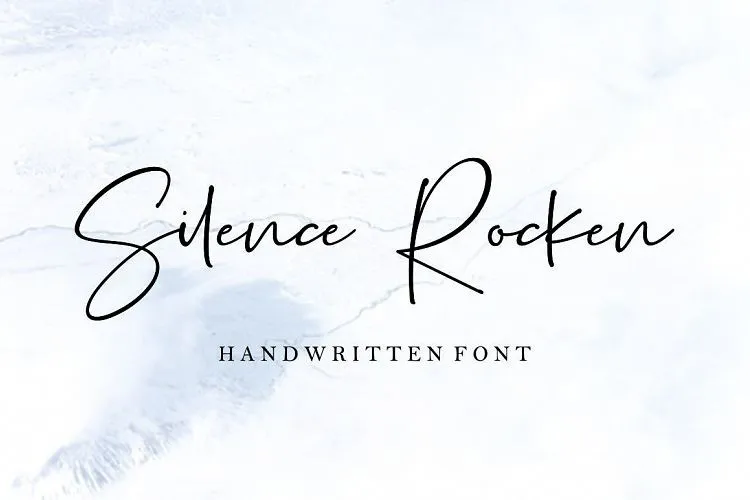
Silence Rocken Handwritten Font – Fonte Grátis
Silence Rocken Handwritten Font
A fonte ‘Silence Rocken Handwritten Font’ é uma criação inovadora do designer fikryal. Ela se destaca na categoria de fonts escritas a mão, trazendo um estilo moderno e sofisticado que encaixa perfeitamente em diversos projetos de design. Esta font pode ser usada com sucesso em variados tipos de materiais como logotipos, marcações, convites, títulos, designs para casamentos, posts nas redes sociais, anúncios, embalagens de produto, etiquetas, fotografias, marcadores de água e eventos especiais. Além disso, ela também serve perfeitamente para designs de revistas e sites. Sem dúvidas, é uma opção ideal para qualquer designer que busca um elemento único e autêntico em seus projetos.